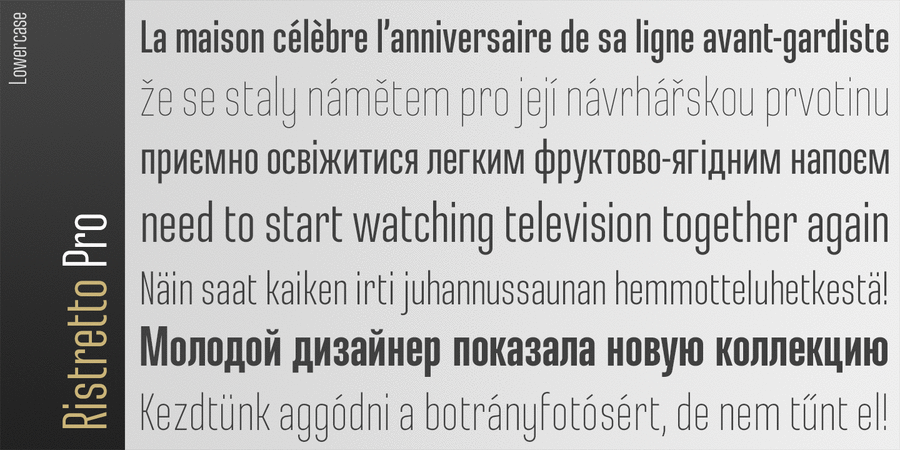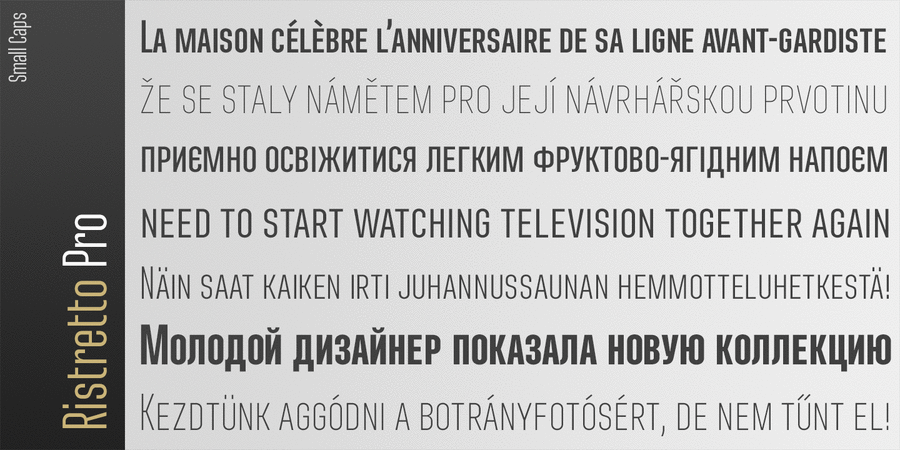
Ristretto Pro – це надвузький акцидентний шрифт, доступний у 8 насиченостях. Гарнітура підтримує безліч мов, 6 наборів цифр та капітель. Ristretto Pro має брускового компаньйона – Ristretto Slab Pro.
Цей шрифт розробив і випустив Андрій Константинов у студії Mint Type у 2013 році.
Хіт 1960-х Ristretto Pro підтримує 83 мовиУкраїнська, Англійська, Німецька, Польська, Португальська, Іспанська, Французька, Російська, Чеська, Голландська, Італійська, Шведська, Турецька, Фінська, Білоруська, Сербська, Болгарська, Естонська, Литовська, Албанська, Африкаанс, Баскська, Бретонська, Валенсаска, Galician, Гельська (Шотландська), Данська, Індонезійська, Ірландська, Ісландська (Win), Каракалпацька, Каталонська, Норвезька, Окситанська, Ретороманська, Самі Лулі, Тсванська, Узбецька (Лат.), Фарерська, фризька, Чаморро, Естонська (Win), Південносаамська, Албанська (Win), Угорська, Верхньолужицька, Карельська, Латвійська (Mac), Литовська (Mac), Маорійські (Mac), Молдавська (Лат.), Нижньолужицька, Румунська (Win), Словацька, Словенська, Туркменська (Лат.), Хорватська (Win), Естонська (Mac), Курдська, Латишська, Маорійські, Руминська, Абазинська, Аварська, Агульська, Адигейська, Даргинську, Інгуську, Кабардино-Черкеська, Кабардинська, Карачаєво-Балкарська, Кумицька, Лакська, Лезгинська, Македонську, Мордовсько-Мокшанська, Мордовсько-Ерзянська, Ногайська, Рутульська, Табасаранська, Татська, Цахурська, Чеченська Функції сімейства шрифтів Ristretto ProЗастосування гарнітури у верстці:
Асоціації з сімейством шрифтів Ristretto ProОсобистість і характер гарнітури:
тонкий, стрункий, худий, рівний, статичний, високий, міський, вузький, технічний, якісний, точний, чіткий, крихкий, прозорий, сучасний, серйозний, монотонний, креслярський, інженерний, архітектурний, стиснений, дорослий, стійкий, стабільний, твердий, гучний, впевнений, помітний, амбітний, важливий, мотивуючий, переконливий, міцний, відповідальний, сильний, робочий, тісний, важкий, суворий, залізний, сталевий, прямокутний, чорний, потужний, гострий